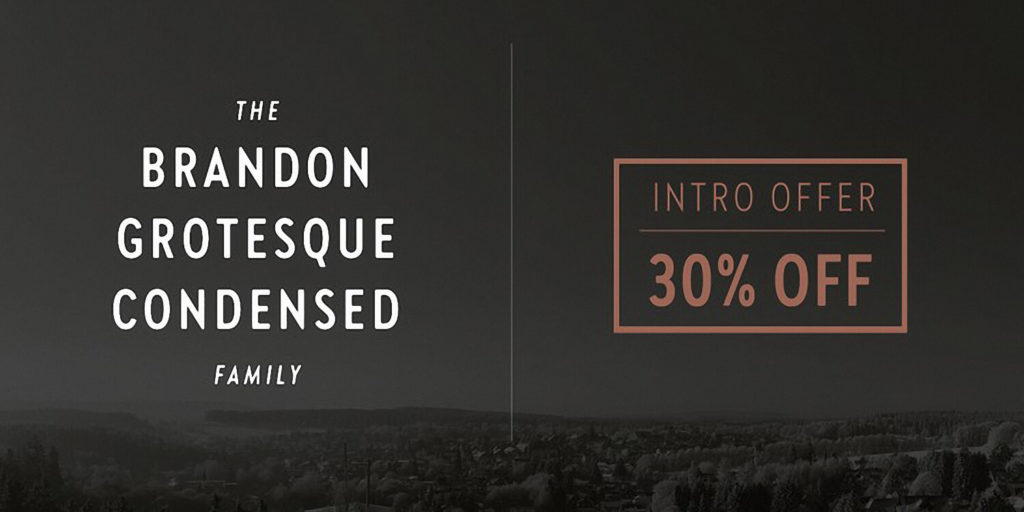
Это суженная версия популярного геометрического гротеска от студии HVD Fonts, созданной дизайнером Ханнесом фон Дёренем в 2018 году. Он объединяет строгую геометрию и современную элегантность, позволяя разместить больше текста в заголовках без потери читаемости. Отлично подходит для логотипов, айдентики и веб-дизайна. Скачать бесплатно можно для личных проектов